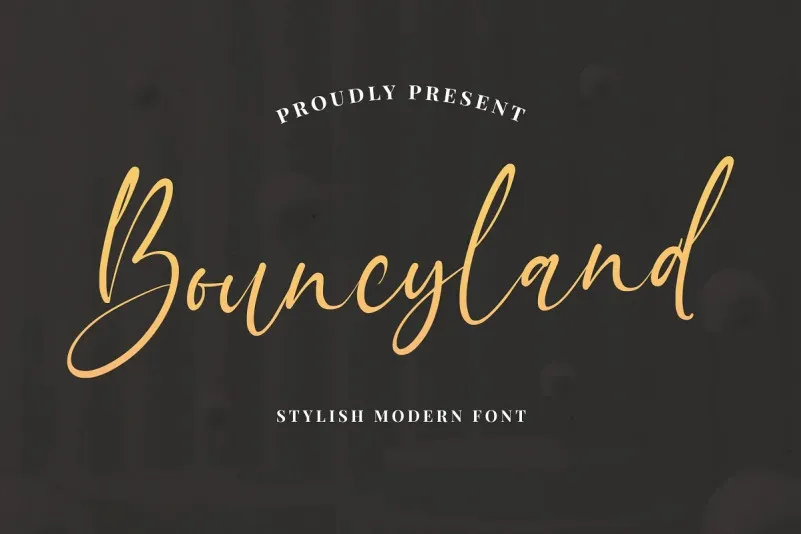
Esta script font ‘Bouncyland Font’ é uma nova variação de uma tipografia criada à mão. Ela está sendo oferecida para que você possa completar sua coleção de fonts script. Esta font artesanal vai adicionar um toque natural encantador a cada detalhe do seu design. É perfeito para qualquer projeto de design, desde convites até logomarcas e capas de livros, ou até mesmo ideias criativas como crafts. Além disso, o fato de ser PUA (Programmed with Alternate) encoded significa que você terá acesso a todas as alternativas de gíria e ligaturas. O Bouncyland Font é uma fonte perfeita para qualquer design projetado com um toque delicado e elegante, mas não menos inovador. Seja em um projeto criativo ou formando uma identidade visual única, esta font trará alegria e vida à sua obra de arte digital. Não espere mais, ele está pronto para entregar o resultado perfeito para todos os seus designs!